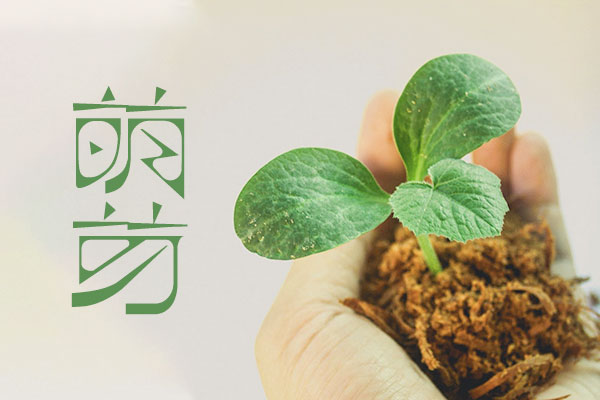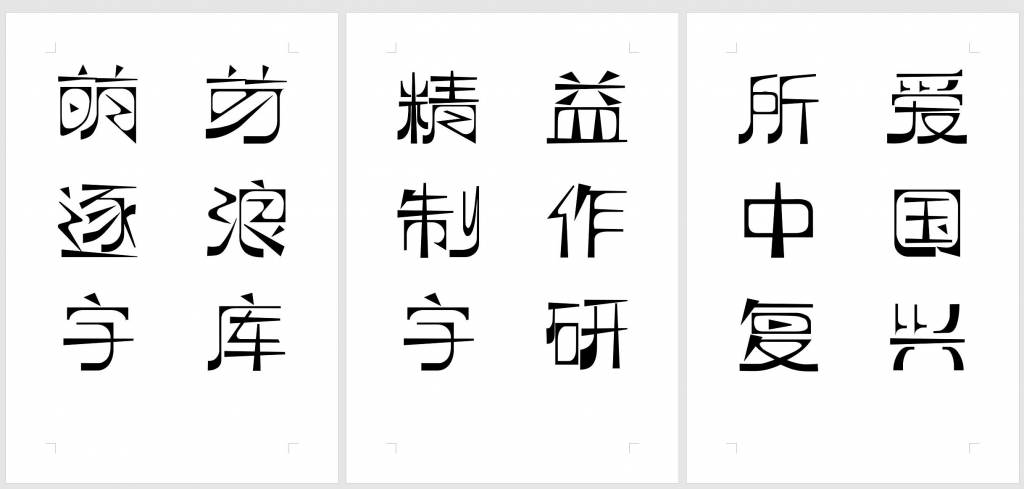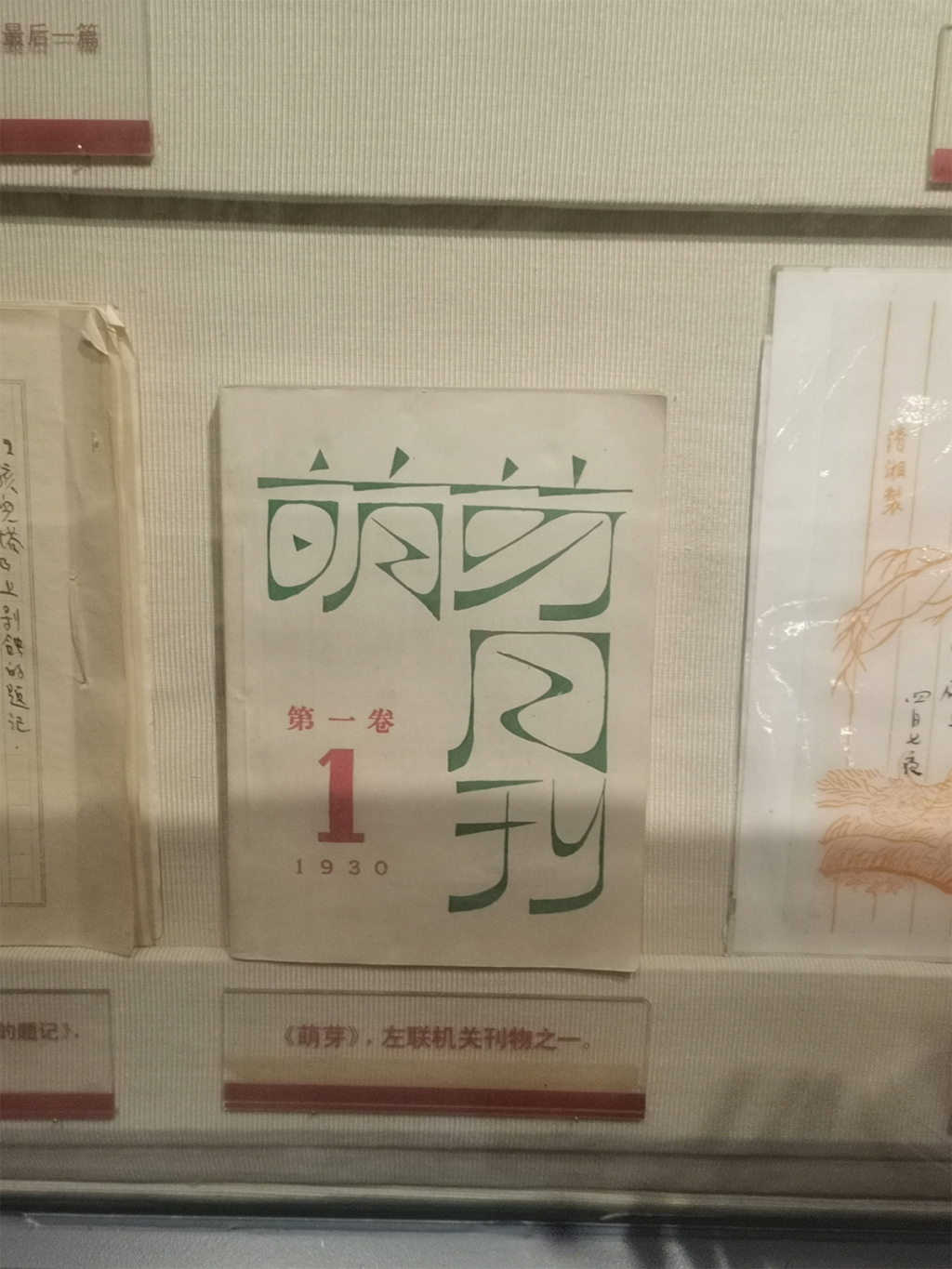
逐浪萌芽字
逐浪萌芽字(Zoomla CMS Fonts)是一款以近代中国共产党《萌芽》月刊为灵感来源的艺术字体。这款字体源自五四运动文化,力求体现近代文艺风格。
逐浪萌芽字的线条呈现外方内圆的格局,具有尖锐的外角和三角部件,内部空间则呈现出圆形切割效果。这种设计反映了五四运动和清末民初时期,在工业革命思维的影响下,一代文化人对中国汉字的探索和创新。字体中的尖锐和锐角三角形部件体现了上进、革命和进击的精神。
结字采用扁形设计,即左右宽度大于上下高度。这种设计使字体在视觉上更加平衡和稳定。
逐浪萌芽字的独特之处在于其外角采用尖角设计,内角则采用弧角设计,使其具有一种抽象的几何美感。字体整体呈现圆形或弧形,具有强烈的视觉冲击力和艺术性。
此外,逐浪萌芽字的笔画粗细对比明显,角的笔画相对横竖线要粗,竖线笔画下端粗上端细,横线笔画左边粗右边细。这种设计使字体更加生动有力,同时也符合现代审美观念。
总之,逐浪萌芽字(Zoomla CMS Fonts)是一款具有独特魅力和历史底蕴的艺术字体。其设计理念源于五四运动文化和《萌芽》月刊,力求体现近代文艺风格。字体线条简洁明了,结字采用扁形设计,笔画粗细对比明显,角的笔画相对横竖线要粗等独特之处使其在视觉上极具冲击力和艺术性。无论是用于书籍出版、广告设计还是个人使用,逐浪萌芽字都能为您的文字内容增添一份别具一格的美感和魅力。
逐浪萌芽字已包含国标规定的简体6763字,简体字还是比较全的。而繁体字的支持则弱一些。